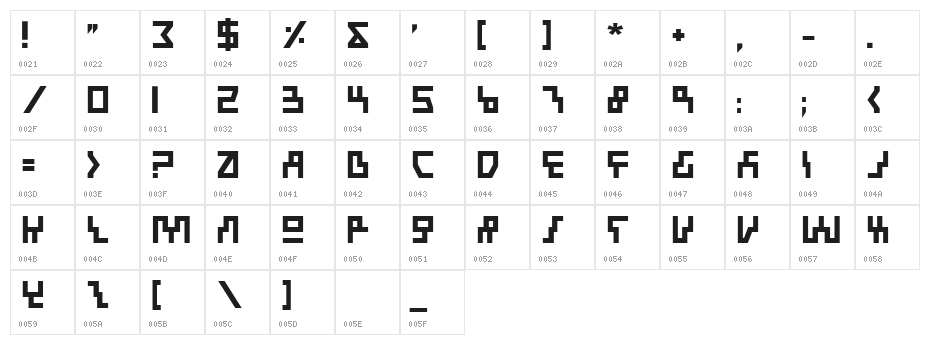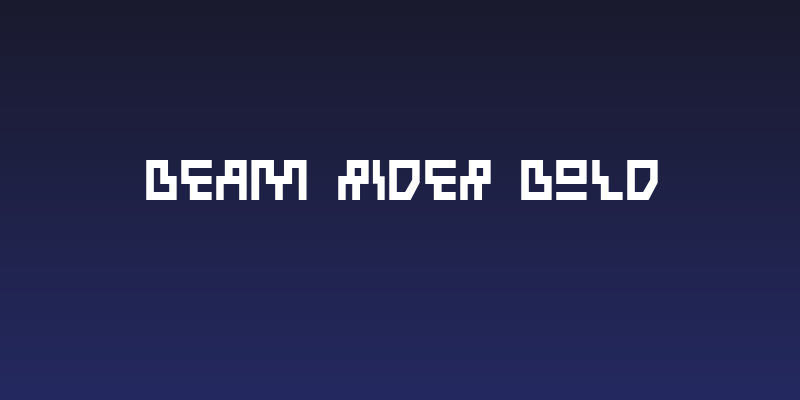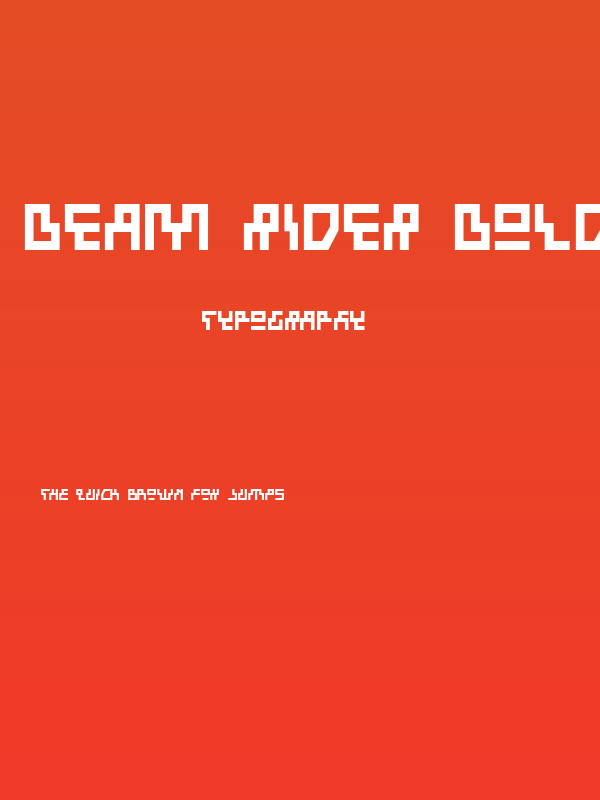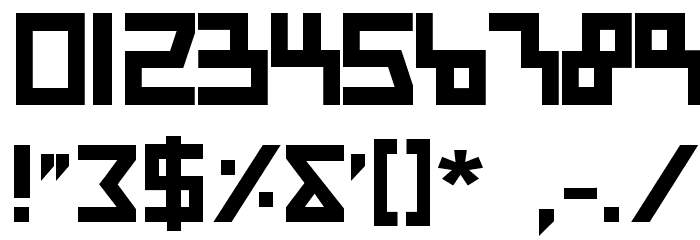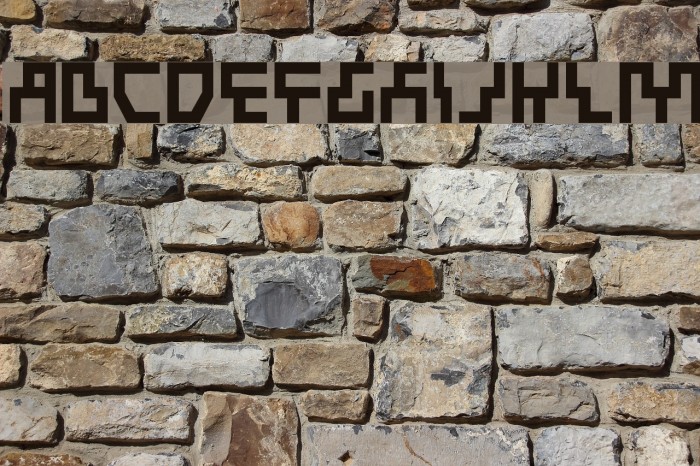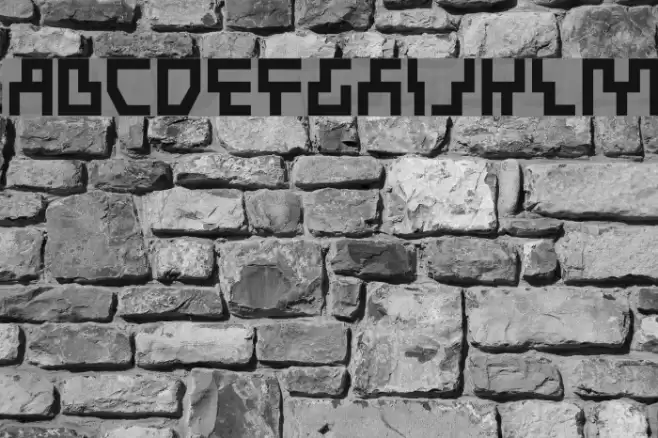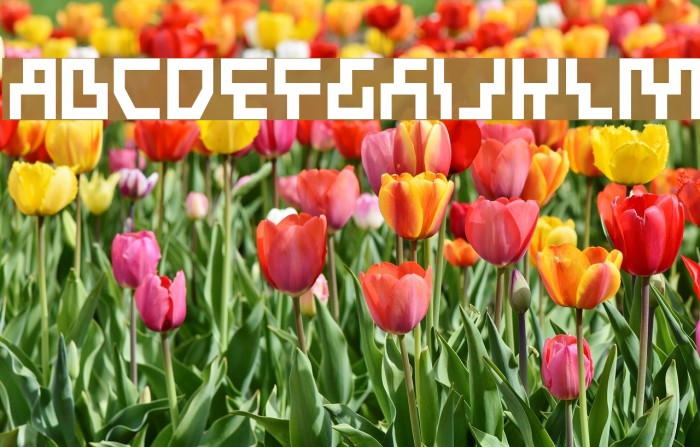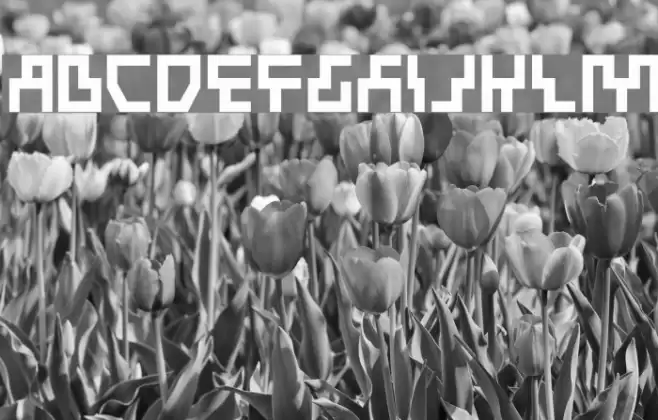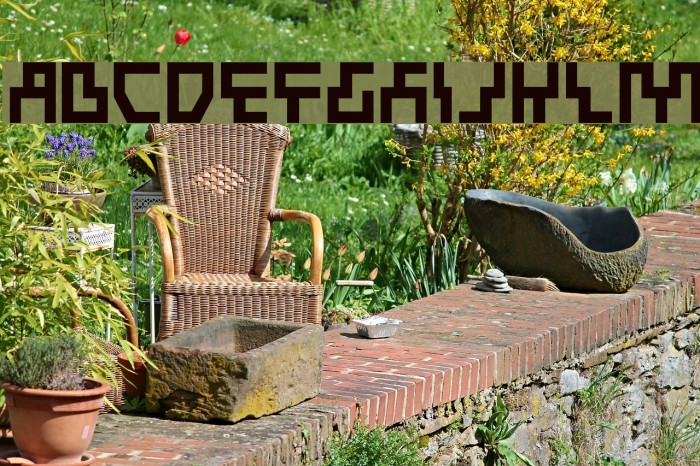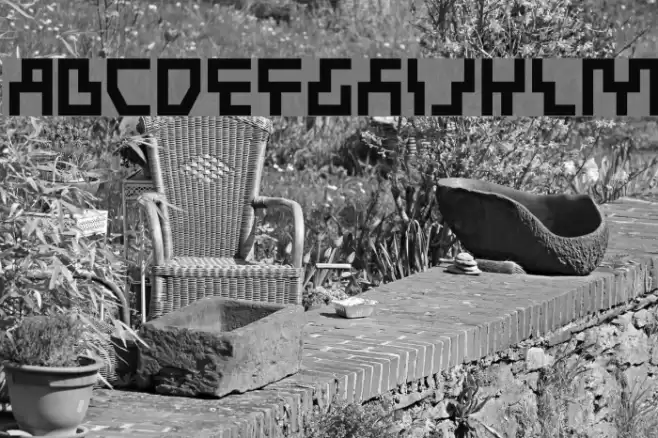
Beam Rider Bold Font
| Proiecte propuse | Ideal for video game titles, tech-themed posters, digital art projects, and branding for technology companies. |